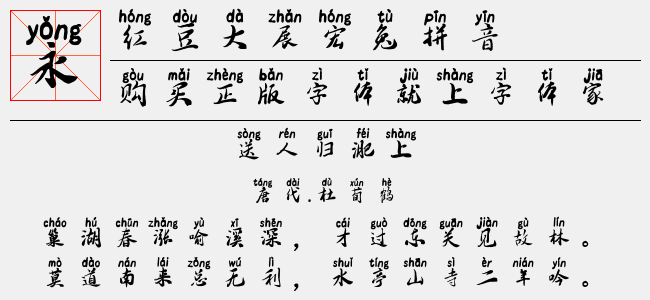
红豆大展宏兔拼音
字体作者:红豆字库
字体名称:红豆大展宏兔拼音
字体家族:红豆字库
书体类型:手写体、印刷体
红豆大展宏兔拼音
红豆大展宏兔拼音是一款非常不错的艺术字体,由红豆字库出品,个性醒目,具有强烈的视觉冲击力,适应于报纸和杂志和书籍中常用字体, 海报、个性促进品牌标志设计、字体设计、等环境使用,欢迎喜欢的朋友前来字体家下载使用。